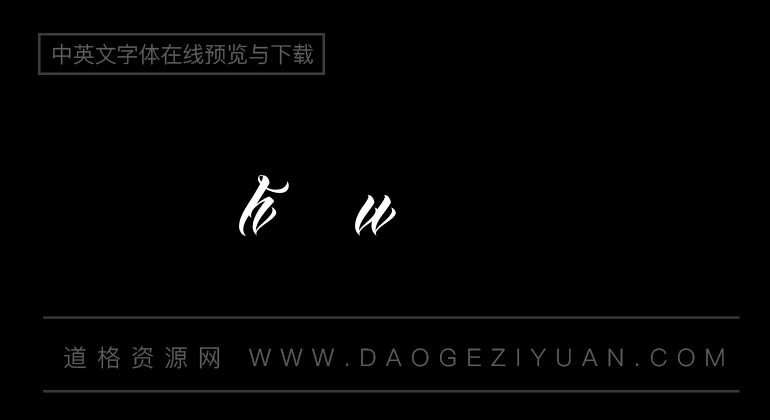
Anha Queen Font 是一款华丽的手写字体,具有独特的连笔风格和流畅的线条。这个字体采用了不规则的字形设计,每个字母都有其独特的魅力。Anha Queen Font 的字形细节非常精细,将每个字母的表现力最大化。该字体适用于各种设计项目,如标题、海报、卡片、T恤等。该字体支持多种语言,包括英语、西班牙语、葡萄牙语、法语、德语、意大利语等。内容介绍
Anha Queen Font是一款非常不错的手写艺术字体,具有很好的视觉感,适合于文化类的宣传设计、商业类品牌的广告和产品包装设计以及个性化文字排版等较多场景。